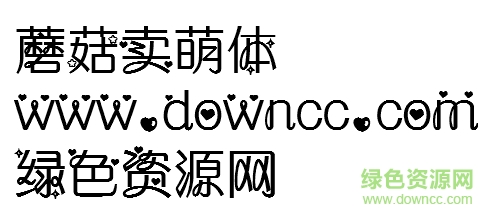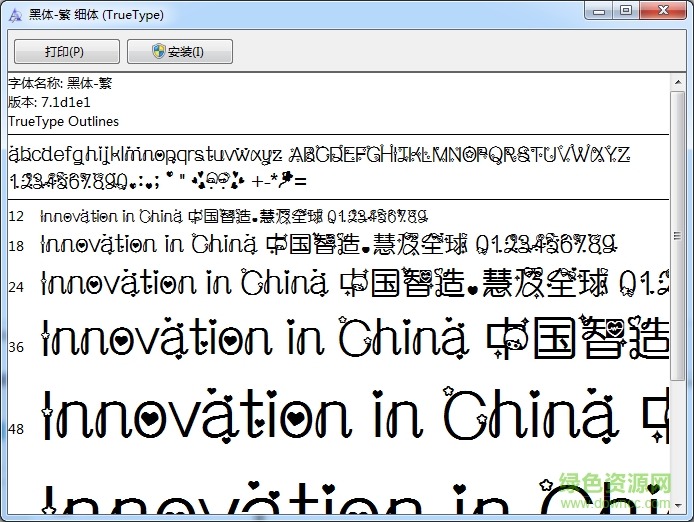
蘑菇賣萌體字體
蘑菇賣萌體是一款十分活潑可愛的藝術(shù)字體,在漢字和字母上都有著不同的星形和心形點綴,在撇捺處也有著流暢的連筆,顯得生動好看,喜歡的朋友就來綠色資源網(wǎng)免費下載吧!
蘑菇賣萌體字體介紹
蘑菇賣萌體是蘑菇街字體推出的一款卡通字體,支持中英文和繁簡體輸入,字庫很豐富,可愛造型和趣味連筆讓你感覺生機勃勃,可廣泛使用于藝術(shù)創(chuàng)意、平面設計、廣告策劃等諸多行業(yè)。
蘑菇賣萌體是以藝術(shù)字體纖蘭體為原形,在字體間嵌入了一些可愛的卡通圖形,纖蘭體端正大方,藝術(shù)美觀,加入卡通圖案后更顯俏皮